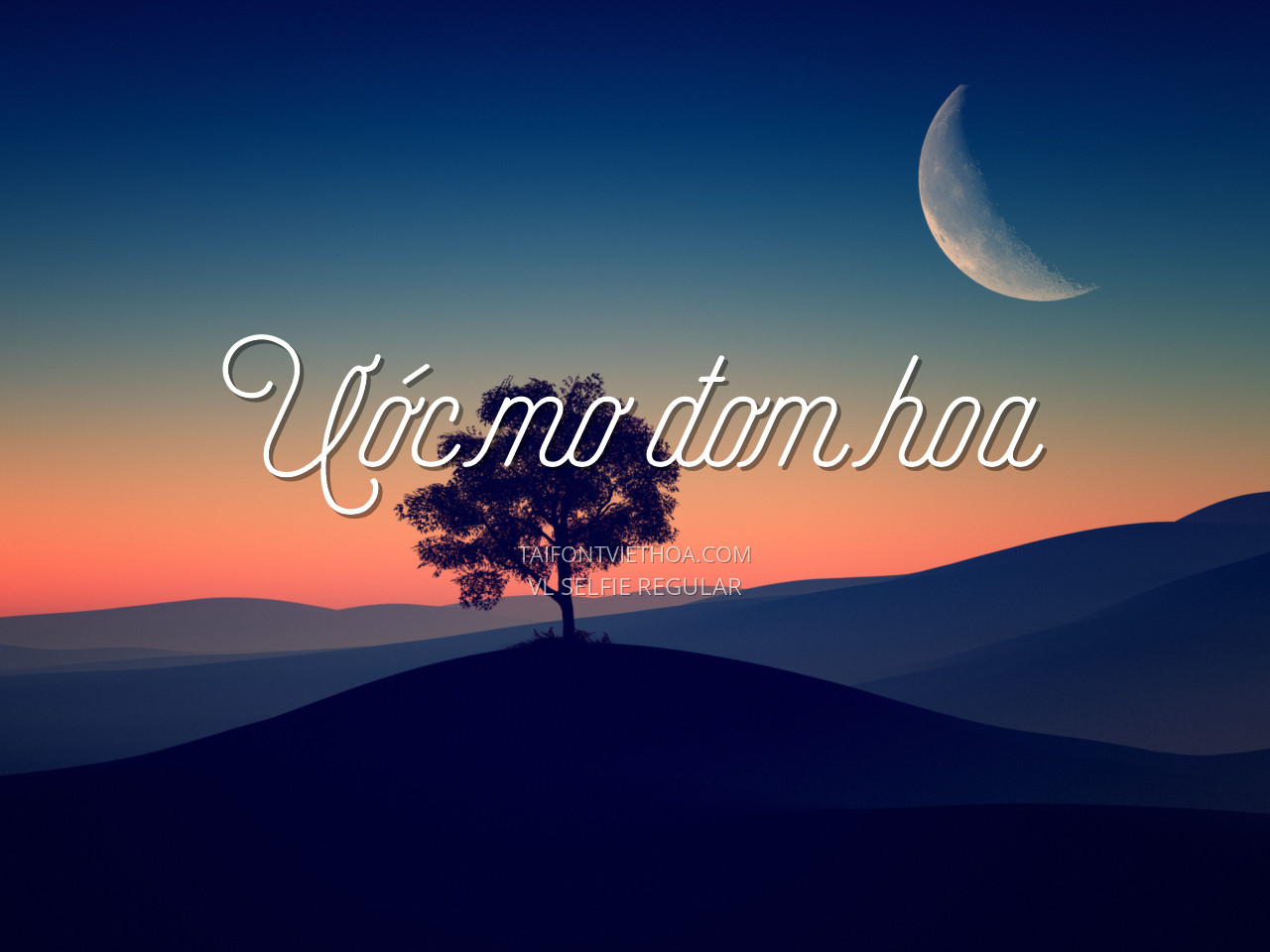
Font việt hóa VL Selfie
Giới thiệu về font VL Selfie
VL Selfie là một kiểu chữ script hiện đại lấy cảm hứng từ các bảng hiệu neon và phong cách retro những năm 70–80. Font sở hữu các nét chữ uốn lượn đầy nghệ thuật, kết nối mềm mại và uyển chuyển, mang lại cảm giác sống động và cá tính. Phiên bản Việt hóa được thực hiện bởi Font Việt Linh, hỗ trợ đầy đủ tiếng Việt với hệ dấu được tinh chỉnh kỹ lưỡng. Ngoài tiếng Việt, VL Selfie còn hỗ trợ hơn 40 ngôn ngữ khác nhờ bảng mã Latin Extended. Font đã được taifontviethoa.com sưu tầm, kiểm thử thực tế và ứng dụng hiệu quả trong các dự án sáng tạo liên quan đến branding, thiết kế retro và truyền thông nghệ thuật.
Đặc điểm thiết kế và ứng dụng của VL Selfie
VL Selfie nổi bật với các đường nét liền mạch, cấu trúc chữ viết tay được vẽ bằng tay tỉ mỉ, tạo hiệu ứng chuyển động mượt mà giữa các ký tự. Phong cách chữ đậm chất vintage nhưng vẫn giữ được sự hiện đại, rất lý tưởng cho các thiết kế cần thể hiện cá tính, sự khác biệt hoặc yếu tố thủ công.
Font phù hợp với thiết kế poster nghệ thuật, tiêu đề retro, bảng hiệu quán cafe, logo thủ công, thương hiệu handmade, bao bì sản phẩm sáng tạo và thiệp mời cá tính. Ngành nghề lý tưởng: ẩm thực, thời trang cá tính, dịch vụ sáng tạo, handmade, spa và thương hiệu cá nhân.
Thiết kế: Zamroni Hamzah
Thiết kế: Roland Hüse Design